Geschichte der Typografie
Die Geschichte der Typografie bietet eine chronologische Übersicht über die Entwicklung der Schriftkultur. In ihrem Mittelpunkt steht heute vor allem die historische Herausbildung der unterschiedlichen Druckschriften.
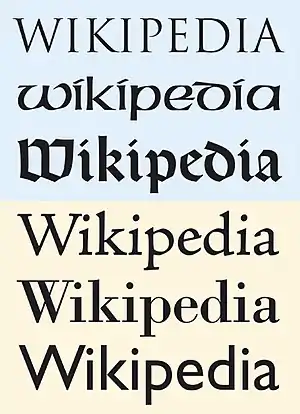
Themen der Typografiegeschichte
- Im Mittelpunkt der Typografiegeschichte steht die historische Herausbildung der unterschiedlichen Druckschriften (Antiqua, Grotesk sowie Displayschriften) bis hin zur heutigen Typografie im Internet. Die Handschriften vor der Erfindung des Buchdrucks hingegen zählt man in der Regel zur Vorgeschichte. Zur historischen Entwicklung der Schrift, siehe auch Geschichte der Schrift und Paläografie.
- Die westliche Typografiegeschichte beschränkt sich naturgemäß auf den Einzugsbereich des lateinischen Alphabets – also West- und Mitteleuropa, Nord- und Südamerika sowie den mittleren und südlichen Bereich des afrikanischen Kontinents. Schwerpunkte sind dabei meist die entwickelten Länder Westeuropas sowie die USA. Zur Entwicklung der unterschiedlichen Alphabete weltweit siehe Schriften der Welt, Alphabet sowie Alphabetschrift.
Ein mit der Geschichte der Typografie eng verwandtes Thema ist die Geschichte des Grafikdesigns sowie die Geschichte der grafischen Stile. Anders als beim Grafikdesign, das allgemeine Gestaltungsgrundsätze thematisiert, steht bei der Typografie mehr der Umgang mit Schriften sowie die typografischen Konventionen im Mittelpunkt. Die Geschichte der Typografie behandelt vor allem
- die historische Entwicklung der Druckschriften,
- technische Innovationen, soweit sie für den Einsatz von Schriften relevant sind (Buchdruck, Blei-, Maschinen- und Fotosatz, Desktop-Publishing; OpenType),
- die historische Herausbildung typografischer Konventionen und Maßsysteme.
Handschriftliche Vorgeschichte der Lateinischen Druckschriften
(siehe ausführlich Paläografie – Geschichte der Lateinischen Schrift)
Vom Aufkommen der Schrift als solcher im Altertum bis zum Beginn des Buchdrucks am Ende des Mittelalters war das Erstellen von Dokumenten und Büchern eine handschriftliche Angelegenheit. Die Gestalt der lateinischen Schrift erfuhr während dieses Zeitraums mehrmalige Veränderungen. Die wichtigsten uns heute bekannten Vorformen der Druckschriften sind: römische Capitalis, frühmittelalterliche Unzialschriften, die Karolingische Minuskel sowie die gotisch-gebrochenen Schriften des Hoch- und Spätmittelalters. Typografiegeschichtlich relevant sind diese Vorformen aus drei Gründen:
- der im Verlauf eines Jahrtausends vollzogenen Zusammenfügung von Groß- und Kleinbuchstaben-Alphabet,
- der formalen Entwicklung hin zu den aktuellen Buchstabenformen und schließlich
- als historisierende Referenzmöglichkeit: Anders als heute noch verwendete Druckschrift-Prototypen wie etwa die Garamond aus dem 16. Jahrhundert dienen digitale Capitalis-, Unzial- oder Textura-Schriften vor allem dazu, historische Epochen typografisch in Szene zu setzen.
Römische Capitalis
Über Etrusker und Griechen gelangten die Vorformen des heutigen lateinischen Alphabets im Verlauf des ersten Jahrtausends v. Chr. zu den Römern. Das römische Alphabet entsprach bereits weitgehend dem heute verwendeten. Allerdings war es ein reines Großbuchstaben-Alphabet. Als Hochschrift des Römischen Reiches gilt heute die Capitalis monumentalis. Bekanntestes historisches Dokument dieser Monumentalschrift sind die Inschriften der 113 n. Chr. errichteten Trajanssäule. Neben den vor allem in Stein gehauenen Monumentalschriften gab es auch informellere Schriftvarianten wie etwa die Capitalis quadrata, die Capitalis rustica sowie die ältere römische Kursive und die jüngere römische Kursive. Neben der Verwendung als Buchschrift dienten sie vor allem dazu, den informellen, alltäglichen Schriftverkehr zu bewältigen.
Unzialschriften
Auch im Römischen Reich unterlagen die Schriften einem langsamen Veränderungsprozess. Die Schriftkultur der Spätantike und des Frühmittelalters war von der Unzialschrift und der Halbunzialen geprägt. Deren Herkunft leitete sich von den informelleren Schreibvarianten der römischen Schrift ab (ältere römische Kursive, jüngere römische Kursive). Im angelsächsischen Bereich wurden für einzelne Laute auch Zeichen aus Runenschriften ergänzt (thorn für th). Die Unzialschrift hat ein Großbuchstaben-Alphabet; die seit dem 3. Jahrhundert verwendete Halbunziale benutzt auch Ober- und Unterlängen, um Buchstaben zu unterscheiden, und besitzt deshalb ein Kleinbuchstaben-Alphabet.
Neben der Unziale und der Halbunziale entwickelten sich aus den römischen Kursiven eine Reihe regionaler Schriftformen. Da sie vor allen lokale Bedeutung genossen, werden sie auch unter dem Oberbegriff Nationalschriften zusammengefasst, wobei ihr Gebrauch nicht ethnisch oder politisch bestimmt ist, sondern vorrangig geografischen Bezug hat. Entwicklungshistorisch sind die Schriften des Frühmittelalters die unmittelbaren Vorläufer der Karolingischen Minuskel.
Die Unziale findet bis heute gern in christlichen Kontexten Verwendung, etwa für Inschriften in Kirchen oder auf Grabsteinen. Moderne Nachinterpretationen der Unzialschrift wie zum Beispiel die American Uncial finden sich im Fantasy-Bereich oder auch in der Esoterik-Szene. Ein bekanntes Einsatzbeispiel ist etwa in der Verfilmung des Tolkien-Bestsellers Der Herr der Ringe zu sehen.
Karolingische Minuskel
Mit Unterstützung der Karolinger, die seit Ende des 8. Jahrhunderts weite Teile Mitteleuropas beherrschten, verbreitete sich die Karolingische Minuskel über ganz Europa. Auslöser für ihre flächendeckende Etablierung waren insbesondere die Bildungsreformen Karls des Großen (die so genannte Karolingische Reform). Am spätesten drang die Schrift in Spanien (Westgotische Minuskel), Großbritannien (Insulare Schriften) und Süditalien (Beneventana, Curialisca) ein.
Die Karolingische Minuskel ist das Vorbild für das Kleinbuchstaben-Alphabet in seiner heute noch gebräuchlichen Form. Die Abschriften antiker Autoren (beispielsweise Horaz, Vergil, Homer) in klösterlichen Scriptorien führte bei den Gelehrten der Renaissance zu der Annahme, es handle sich bei der Karolingischen Minuskel um die originale Schrift der Antike. Ab dem 14. Jahrhundert entstand so auf Basis der Karolingischen Schriften in Italien die Humanistische Minuskel, die zur Vorlage der ersten Renaissance-Druckschriften (Venezianische Renaissance-Antiqua, ab etwa 1470) wurde. In Abgrenzung zu den zeitgenössischen hochmittelalterlichen Schriften (der Textura und der Rotunda) wurde diese Schriftneuschöpfung als „antik“ (lateinisch antiquus) bezeichnet, um sie so gegenüber den später entstandenen Schriften abzugrenzen. Hiervon leitet sich der Begriff „Antiqua“ ab.
Gotische Schriften
Aus der spätkarolingischen Minuskel entwickelten sich im Hochmittelalter die Buchschriften der Gotik. Ihre zahlreichen Varianten zeichneten sich alle durch ein regelmäßiges, strenges, eng geschriebenes Schriftbild aus. Die Rundungen der Buchstaben wurden gebrochen, weshalb diese Schriften auch – insbesondere auch zwecks Unterscheidung zu den später entstandenen Antiqua-Schriften – als gebrochene Schriften bezeichnet werden. Das Hauptmerkmal der gotischen oder gebrochenen Schriften war ein enges, dunkles Schriftbild, das in seiner strukturartigen Form stark an gewebte Stoffe erinnert; daher leitet sich auch der Name Textura für die bekannteste Schrift dieser Epoche ab.
Parallel entwickelte sich in Italien, Spanien und in geringerem Maße in Deutschland eine alternative Form der gotischen Schrift: die Rotunda oder Rundgotische. Bei der rundgotischen Schrift sind die Formen weiter und die Buchstaben besitzen statt der harten Winkel Rundungen. Dies machte die Schrift lesbarer. Beide Schriftarten wurden von den frühen Druckern der sogenannten Inkunabelzeit übernommen. Bis Mitte des 16. Jahrhunderts wurden sie allerdings weitestgehend von anderen Schriften verdrängt.
Eine weitere Entwicklung der hochmittelalterlichen Gotik waren Vorformen der heutigen Kursivschriften. Schräg geschriebene (also: kursive) Schriften wurden dem Gebrauch in Büchern angepasst und so zu den sogenannten Bastarda-Schriften weiterentwickelt. In Mitteleuropa bildete sich als Weiterführung der Textura zum Ende des Mittelalters die Fraktur heraus. Die zu Beginn des 16. Jahrhunderts entstehenden Frakturschriften waren erfolgreich und lieferten auch die Vorbilder für die Schriftentwürfe von Albrecht Dürer und Johann Schönsperger. Eine derbe, volkstümliche Fortentwicklung der Textura ist die Schwabacher, die ebenfalls zu Beginn des 16. Jahrhunderts entstand. Zusammen mit der Fraktur bestimmte sie das Druckbild in Deutschland bis hinein ins 20. Jahrhundert. In den Ländern um das Mittelmeer, dem Hauptverbreitungsgebiet der Rotunda, setzen sich hingegen die Antiqua-Schriften durch.
Geschichte der Druckschriften bis zum 20. Jahrhundert
Anders als die bislang beschriebenen historischen Schrifttypen sind die ab der frühen Neuzeit entwickelten Schriften keine geschriebenen Schriften, sondern Druckschriften. Das Hauptmodell, die ab circa 1450 aufkommende Antiqua, bildet bis auf den heutigen Tag die Grundlage aktuell verwendeter Schriften. Die Feinausgestaltung der Antiquaschriften hingegen durchlief seit der Renaissance-Ära mehrere Entwicklungsstadien. Die Schriftklassifikation unterteilt diese in die Hauptgruppen Renaissance-Antiqua, Barock- oder Übergangsantiqua sowie klassizistische Antiqua. Ab dem 19. Jahrhundert kamen als weitere Schrifttypen serifenbetonte linear Antiqua sowie serifenlose Groteskschriften hinzu.
Entstehung der Antiqua
Im Zuge der Frührenaissance erwachte auch das Interesse an den Schriftformen der Antike neu. Mittelpunkt der Entwicklung war Italien. Anders als im Norden hatte sich hier früh das gemäßigt gotische Modell der Rotunda etabliert. Gutenbergs 42-zeilige Bibel von 1455 hatte noch die besten gotischen Handschriften zum Vorbild. Bereits zehn Jahre später erkannten deutsche Druckmeister in Subiaco (Italien) sowie venezianische Nachfolger wie Nicolas Jenson und Aldus Manutius, dass die neue Technik auch eine andere Formgestaltung ermöglichte. Nach dem Vorbild italienischer Humanistenhandschriften vereinigten sie die „überarbeiteten“ Kleinbuchstaben der karolingischen Minuskel mit den Großbuchstaben der römischen Capitalis. Dadurch entstand eine Zweialphabetschrift, die sich von den gebrochenen Schriften des Hochmittelalters klar abhob – die sogenannte „Antiqua“.
Das Bild der ersten Antiquaschriften war noch stark von mittelalterlichen, gotischen Elementen geprägt. Auch die Entwicklung hin zur heute gebräuchlichen Groß- und Kleinschreibung vollzog sich erst langsam im Lauf der folgenden Jahrhunderte und von Land zu Land verschieden. Zusätzlich integrierten die Schriftentwerfer und Stempelschneider der Renaissance zwei weitere Zeichen-Komponenten in ihre zeitgenössischen Schriften: zum einen das arabische, ursprünglich aus dem indischen Raum stammende Ziffernsystem, zum zweiten Kursivschriften. Bei Letzteren handelte es sich um Bastarda-Varianten, welche einige Schreibmeister des ausgehenden 15. Jahrhunderts an das Erscheinungsbild der Antiqua anglichen. Die auch als „Italics“ bezeichneten Antiqua-Kursiven entwickelten sich erst im Verlauf der folgenden Jahrhunderte zu integrierten Schriftschnitten kompletter Schriftfamilien.
Renaissance (1400 bis 1600)
Die Renaissance-Antiqua (andere Bezeichnungen: Old Style-Antiqua oder auch ältere Antiqua) lässt sich in zwei stilistisch klar voneinander abgrenzbare Gruppen aufgliedern: die Venezianische Renaissance-Antiqua und die Französische Renaissance-Antiqua.
Bei der venezianischen Renaissance-Antiqua, deren Stilmerkmale sich ungefähr zwischen 1455 und 1485 entwickelten, ist die Ableitung von spätmittelalterlichen Rotunda- und Bastarda-Schriften noch mehr oder weniger stark zu erkennen. Bekanntestes Exponat dieser Gruppe ist die von Nicolas Jenson um 1470 geschaffene Jenson Antiqua; eine zeitgemäße Interpretation ist die 1996 entstandene Adobe Jenson von Robert Slimbach. Die Strichstärken dieses Typs sind relativ einheitlich. Die kalligrafische Zeichnungsweise tritt klar hervor. Anders als spätere Antiquaschriften erwecken Frühantiquas dieses Typs einen mehr oder weniger stark ausgeprägten historisierenden, spätmittelalterlichen Eindruck und kommen daher im heutigen Satz eher seltener zum Einsatz.
Ihre heute noch gültige, klassische Form erreichte die Antiqua mit dem venezianischen Verleger Aldus Manutius und seinem Stempelschneider Francesco Griffo. Die nach einem zeitgenössischen Kardinal benannte und um das Jahr 1495 entstandene Bembo gilt als der Prototyp dieser Phase. Vor allem im Buchsatz kommt sie bis heute regelmäßig zur Anwendung. Eine weitere Innovation von Griffo war die Entwicklung der Kursivschrift. Insgesamt werden die zwischen Ende des 15. und Anfang des 16. Jahrhunderts geschaffenen Schriften, obwohl großteils in Italien entstanden, bereits dem Modell der Französischen Renaissanceantiqua zugerechnet. Einige Schrifthistoriker bezeichnen die italienischen Schriften der Frühneuzeit auch als „Aldinen“ – als Abgrenzungsbegriff zu den im 16. Jahrhundert entstandenen Typ der Garalden, welcher die Schriften aus der Ära Claude Garamonds charakterisiert.
Der Pariser Stempelschneider Claude Garamond (1499 bis 1561) gilt heute als bekanntester Vertreter der französischen Renaissance-Antiqua. Bis zum Jahr 1600 war die von ihm entworfene Schrift zur vorherrschenden Buchschrift in Europa geworden. Sie zeichnet sich durch ein ruhiges, harmonisches und helles Schriftbild aus und hat ausgeprägte Ober- und Unterlängen. Wegen ihrer formalen Qualitäten und guten Lesbarkeit wird sie auch heute noch oft verwendet und in unterschiedlichen Nachschnitten von zahlreichen Schriftherstellern angeboten. Ein Zeitgenosse Garamonds war der in Lyon ansässige Stempelschneider Robert Granjon (1513 bis 1589). In Anlehnung an historische Schreibschriften versuchte Granjon unter anderem das ambitionierte Schriftprojekt Lettre de Civilité. Die als neue französische Allgemeinschrift geplante Civilité scheiterte allerdings aufgrund mangelnder Akzeptanz.
Barock (1600 bis 1760)
Zu Beginn des 17. Jahrhunderts verlagerte sich das Zentrum der Schriftentwicklung zunehmend in die Niederlande. Maßgebliche Initiatoren waren die beiden Kaufleute und Verleger Christoffel Plantijn (1520 bis 1589) sowie der 1540 geborene Louis Elzevir. Der in Antwerpen ansässige Plantijn besorgte sich zahlreiche Matrizen und Vorlagen aus der Hinterlassenschaft Garamonds; angestellt war bei ihm unter anderem der französische Stempelschneider Jakob Sabon (oder Jacques Sabon; * 1535, † zwischen 1580 und 1590). Für das von Elzevir gegründete Unternehmen in Leiden (später: Den Haag) arbeitete unter anderem Christoffel van Dijck (1601 bis 1699), einer der bedeutendsten Stempelschneider seiner Epoche. Weitere maßgebliche Schriftentwerfer des 17. Jahrhunderts sind der Deutsche Anton Janson sowie der Ungar Mikolós Tótfalusi Kis (auch Miklós Tótfalusi Kis oder Nicholas Kisz; 1650–1702). Für das 18. Jahrhundert ist schließlich der Nürnberger Johann Michael Fleischmann (1701–1768) aufzuführen, der zeitweilig ebenfalls in den Niederlanden tätig war.
Allgemein vollzog sich der Übergang zwischen den Schriften Garamonds und den holländischen Antiquaschriften langsam und kontinuierlich – weswegen die Schriften dieser Epoche auch als Übergangsantiqua bezeichnet werden. Die niederländischen Schriften wirkten einfach, oft derb-robust und erwiesen sich vor allem als gebrauchstüchtig. Digitale Nachschnitte der Schriften von Janson, Van Dijck, Kisz und Fleischmann kommen im Buchsatz ebenfalls nach wie vor regelmäßig zur Anwendung. Die Plantin, eine Reminiszenz an die niederländischen Barockschriften von dem US-amerikanischen Schriftentwerfer Frank Hinman Pierpont (1860–1937) aus dem Jahr 1913, diente schließlich als Vorlage beim Entwurf der wohl bekanntesten Barockantiqua überhaupt – der 1931 bis 1935 entstandenen Times.
Im Vergleich zu den älteren Renaissance-Antiquaschriften wirken die niederländischen und britischen Übergangsantiqua des 17. und 18. Jahrhunderts zum einen nüchterner. Zum anderen treten die Kontraste zwischen Grund- und Haarstrichen allmählich mehr und mehr in den Vordergrund; die Schriften wirken insgesamt kontrastreicher. Ein wesentlicher Grund für diese Entwicklung: Anders als bei den mit der Breitfeder gezeichneten Schriftentwürfen des 16. Jahrhunderts ließen sich die Schriftgestalter des 17. und 18. Jahrhunderts immer stärker von den präzisen Formen zeitgenössischer Kupferstiche inspirieren.
Formal zum Abschluss gebracht wird die Barock- oder Übergangsphase der Antiqua durch die britischen Schriften des 18. Jahrhunderts. Anfangs orientierten sich deren Gestalter stark an holländischen Vorbildern. Bekanntester Schriftentwerfer dieser Epoche war William Caslon. Stilistisch gesehen brachten Caslons Schriften wenig Innovationen. Dafür waren sie beliebt und schließlich so verbreitet, dass sie sowohl beim britischen Königshaus Anwendung fanden als auch bei der Abfassung und Verbreitung der US-amerikanischen Unabhängigkeitserklärung. Caslons Epigone war der britische Drucker und Stempelschneider John Baskerville. Im Unterschied zu Caslon galt Baskerville als Perfektionist; seine kontraststarken, stark vom Kupferstich geprägten Schriften wie die Baskerville beeinflussten schließlich auch die klassizistischen Schriftentwerfer stark.
Klassizismus (1760 bis 1830)
Im Klassizismus erreichte die Entwicklung der Antiqua ihren vorläufigen Endpunkt. Die Buchstaben wurden aufgrund der technischen Weiterentwicklung immer kontrastreicher, die Serifen immer zarter. Schriften wurden mit Lineal und Zirkel konstruiert, um dem Ideal von Klarheit und Norm zu genügen. Aufgrund dessen sind sie aber auch wesentlich schwerer zu lesen als ihre Vorgänger aus der Renaissance und dem Barock. Blocksatz und Mittelachse blieben als Formen der Typografie weiterhin erhalten. Aufgabe der Typografen war die Wahl einer passenden Schrift und die Strukturierung des Textes. Buchschmuck wurde sparsam eingesetzt. Üppig illustrierte Initialen wichen Initialen in der Grundschrift. Am Ende des Klassizismus tauchten die ersten Grotesk- und Egyptienne-Schriften auf. Eine weitere Innovation dieser Ära war schließlich die Etablierung des typografischen Punktsystems.
Die bedeutendsten Schriftentwerfer der Epoche waren der Italiener Giambattista Bodoni, die französische Stempelschneiderfamilie Didot sowie der Deutsche Justus Erich Walbaum. Insbesondere Bodonis Schriften, dokumentiert in dem nach seinem Tod herausgegebenen Manuale Tipografico, gelten aufgrund ihrer Präzision und ihrer Eleganz als herausragend. Firmin Didots gleichnamige Didot hingegen wird wegen ihrer abgespeckt-kühlen, oft auch als kalt charakterisierten Präzision als die Schrift der französischen Aufklärung bezeichnet. Darüber hinaus dominierte das Familienunternehmen Didot mit seinen Schriften und Gestaltungen die französische Typografie bis weit ins 19. Jahrhundert. Die Walbaum, der dritte Prototyp der klassizistischen Ära, wird hingegen oft als gemütlich, negativ auch als biedermeierlich beschrieben. In Deutschland avancierte sie indes zur maßgeblichen Schrift der klassizistischen und romantischen Epoche.
Die Gestaltungsmerkmale klassizistischer Antiquaschriften wurden zu Anfang des 19. Jahrhunderts auch auf das Erscheinungsbild der Fraktur übertragen, die das typografische Erscheinungsbild in Deutschland weiterhin maßgeblich prägte. Neben Walbaum war an dieser stilistischen Erneuerung auch der Drucker Johann Friedrich Unger beteiligt. Walbaum Fraktur und Unger Fraktur entwickelten sich schließlich zu Vorbildern für weitere Frakturentwürfe der Wilhelminischen Ära, wie zum Beispiel die Fette Fraktur oder die 1911 entstandene Wilhelm Klingspor Gotisch. Auch bei anderen Schrifttypen wie zum Beispiel den aus den Kanzleischriften hervorgegangenen Schreibschriften wurden die klassizistischen Einflüsse immer unübersehbarer. In der ersten Hälfte des 19. Jahrhunderts tendierte die klassizistische Typografie immer stärker zu rein formalen und immer ausgeschmückteren Lösungen. Stilgeschichtlich mündete die klassizistische Phase der Typografie schließlich in den stark mit Pomp und Pathos aufgeladenen Historizismus der Viktorianischen Epoche.
Die Ära der Industrialisierung (1830 bis 1890)
Das 19. Jahrhundert brachte stilistisch wenig grundlegende Innovationen. Die wesentliche Neuerung war das Aufkommen serifenverstärkter Schriften. Vorläufer waren sogenannte Egyptienne-Schriften, die bereits zu Anfang des 19. Jahrhunderts verstärkt zum Einsatz kamen. Ihr Name leitet sich vermutlich aus der Orientbegeisterung der napoleonischen Ära ab, die wiederum durch den Ägyptenfeldzug Napoleons ausgelöst worden war. Serifenverstärkte Schriften wie zum Beispiel die Clarendon aus dem Jahr 1845 hingegen waren in der Regel Zeitungsschriften, deren Serifen verstärkt wurden, damit sie im Druck nicht ausbrachen. Stilistisch wirkten die Serifenverstärkten der Jahrhundertmitte sehr robust und wiesen ansonsten meist mehr oder weniger starke klassizistische Gestaltungsmerkmale auf. In der Folgezeit änderte sich dies: Durch das Übertragen der Gestaltungsmittel Serifenverstärkung und Serifenanhängung auf immer mehr Schrifttypen bildete sich im Verlauf des 20. Jahrhunderts nach und nach eine eigenständige Zwischengruppe in sich recht heterogener Schriften heraus. Mittlerweile werden Slab Serifs oder Serifenverstärkte in den meisten aktuellen Schriftklassifizierungssystemen als eigenständige Gruppe geführt – neben den beiden anderen Hauptgruppen Serif (traditionelle Antiqua-Schriften) und Sans Serif (serifenlose Groteskschriften wie zum Beispiel die Helvetica).
Innovativ war das 19. Jahrhundert vor allem in technischer Hinsicht. Maschinelle Fertigungsprozesse veränderten sowohl den Druck als auch die Illustrationsgrafiken. Das Bebildern von Drucksachen ließ sich erheblich standardisieren durch die von Alois Senefelder erfundene Technik der Lithografie. Eine weitere Erfindung war schließlich die Fotografie, deren Etablierung Ende des Jahrhunderts zu den ersten einfachen Rasterungs- und Reproduktionsverfahren führte. Für eine wachsende Nachfrage nach Druckprodukten sorgte die allmähliche Herausbildung einer modernen Massengesellschaft. Dies führte in der Buchgestaltung oftmals dazu, dass sich das Buch als Massenprodukt in seiner Typografie an den Handwerksstücken des Barock orientierte. Eine überreiche Ausstattung mit Zierelementen zeugt davon. Neben dem traditionellen Buchdruck entwickelten sich Ansätze einer Zeitungslandschaft sowie ein breiter Markt für Publikationen, Werbedrucke und Plakate jeglicher Couleur. Die Herausforderungen hatten sich gewandelt: Waren Druck und Typografie jahrhundertelang ein überschaubares Handwerk geblieben, hatten sie sich nunmehr den Herausforderungen einer industriell bestimmten Massengesellschaft zu stellen.
Blei- und Fotosatz im 20. Jahrhundert
Die rund 90 Jahre zwischen 1890 und 1980 prägen das Bild der Typografie bis in die Gegenwart hinein. Das Druckhandwerk wurde zur Industrie, und auch die Typografie wurde zu einem Teil davon. Sowohl stilistisch als auch technologisch verlief diese Epoche teilweise recht turbulent. Maßgeblich waren dabei folgende neuen Entwicklungen:
- Herstellung und Anwendung von Schriften wurden immer stärker von industriellen Fertigungsmethoden bestimmt. Wesentliche Stationen dieses Prozesses waren die Erfindung der Bleisatzmaschine durch Ottmar Mergenthaler (Linotype-Modell, 1886) und Tolbert Lanston (Monotype-Modell, 1887), einige Jahrzehnte später das Aufkommen des Fotosatzes. Folge: Erfassung und typografische Gestaltung des Textes ließ sich in immer stärkerem Maß über tastaturgesteuerte Mechanismen vornehmen anstatt von Hand.
- Ein Folgeaspekt des Industrialisierungsprozesses war die bis dahin ungekannte Anzahl und Verbreitung neuer Schriften. Ob digitale Varianten von Garamond und Bodoni oder neue, zeitgemäße Schriftentwürfe wie Futura, Times und Helvetica: Fast alle aktuell verwendeten Schriften stammen entweder aus der anschließenden und bis heute andauernden Computersatz-Ära oder basieren auf Entwürfen dieser Epoche. Grundlage war die Herausbildung großer Schriftgießereien und Schrifthersteller. Folge: Erfolgreiche Schriften konnten so rasch den Status einer Markenware erlangen – und waren damit wiederum in der Lage, ihrerseits Produkten oder Publikationen ein unverwechselbares „Branding“ zu verleihen.
- Neben der traditionellen Buchtypografie entwickelte sich das Grafikdesign als mehr oder weniger eigenständige Sparte. Das nicht spannungsfreie Wechselverhältnis dieser beiden Sparten bestimmte auch die stilistische Entwicklung der Typografie des 20. Jahrhunderts nicht unmaßgeblich mit.
Jugendstil und Neue Buchkunst
Die modernen Kunststile seit dem Impressionismus fanden auch in der Grafik und der Typografie ihren Widerhall. Populär wurde ab 1890 der Jugendstil. Seine floralen Zierelemente, die geschwungenen Formen sowie die grafikbetonte Ausführung inspirierten auch die Schriftentwerfer der Jahrhundertwende. Eine bekannte Jugendstil-Schrift war die Eckmann, entworfen vom Grafiker Otto Eckmann; darüber hinaus äußerte sich der Jugendstil-Einfluss auch in zahlreichen Buchillustrationen und Exlibris-Gestaltungen.
Insgesamt machte sich um die Jahrhundertwende eine Rückbesinnung zu den Wurzeln der Buchkunst immer stärker bemerkbar. Angestoßen wurde diese von dem britischen Typografen, Sozialisten und Kleinpressen-Verleger William Morris sowie von dem sich auf ihn berufenden Arts and Crafts Movement. Im Wesentlichen initiierte diese Bewegung drei Dinge: eine Rückbesinnung auf die Antiqua-Modelle der Renaissance, Klarheit und Einfachheit in der Buchillustration sowie überschaubare handwerkliche Prozesse bei der Erstellung von Drucksachen. Eine unmittelbare Folge des Arts and Crafts-Bewegung war die Entstehung einer Kleinpressenbewegung, die mehr oder weniger den Morris’schen Idealen verpflichtet war und deren Überbleibsel teilweise bis in die Gegenwart herüberragen. Ein etablierter Treffpunkt dieser Szene in Deutschland ist etwa die Mainzer Minipressen-Messe, die aktuell im zweijährlichen Turnus stattfindet.
Stark vom Arts and Crafts-Movement beeinflusst war insbesondere die Strömung der Neuen Buchkunst, die sich im Jahrzehnt vor dem Ersten Weltkrieg herauszubilden begann. Die jungen Schriftentwerfer der Vorkriegszeit, darunter Fritz Helmuth Ehmcke und Friedrich Wilhelm Kleukens, verwarfen sowohl den typografischen Spätklassizismus als auch den Zierrat des populären Jugendstils. Neues Ideal wurde eine aufgeräumte, schnörkellose und stark den Ideen der Renaissance verpflichtete Buchtypografie. Walter Tiemann in Leipzig, F. H. Ernst Schneidler in Stuttgart und Rudolf Koch in Offenbach waren als Ausbilder die maßgeblichen Mentoren dieser Form der Typografie. Im Buchsatz blieb sie bis weit nach dem Zweiten Weltkrieg bestimmend.
Siehe auch: Buchkunstbewegung
Etablierung der Groteskschriften
Der Beginn des 20. Jahrhunderts war auch die Geburtsstunde des bis heute letzten wichtigen Schrifttyps: der serifenlosen Grotesk. Ihr Ursprung lässt sich zwar bis zum Ende des 18. Jahrhunderts zurückverfolgen, flächendeckend eingesetzt wurden Groteskschriften jedoch erst seit dem Aufkommen der Werbung. Dass der neue Schrifttyp auf viele Zeitgenossen polarisierend wirkte, stellt insbesondere die noch aus dem frühen 19. Jahrhundert stammende Bezeichnung „Grotesk“ unter Beweis. Zwei frühe Grotesk-Modelle waren die von der Berliner Schriftgießerei Berthold in Serie gegebene Akzidenz Grotesk von 1904 sowie die US-amerikanische Franklin Gothic von Morris Fuller Benton. Ähnlich wie bei den Antiqua-Schriften entwickelten sich auch bei der Grotesk mit der Zeit unterschiedliche Design-Richtungen:
- eine stark an der klassizistischen Formenlehre orientierten Schule. Zu ihr zählen neben den beiden erwähnten Schriften vor allem die Helvetica, die Arial und die Univers. In seiner reinsten Form ist dieser Gestaltungsstil bei den drei letzten Schriften zu beobachten; zeitlich gesehen überschneidet er sich stark mit der zeitweiligen Dominanz helvetischer Gestaltungskonzepte in den 1950er und 1960er Jahren. Als gemäßigte Form dieser Richtung gilt die Amerikanische Grotesk wie zum Beispiel die Franklin Gothic.
- eine von der Renaissance-Antiqua abgeleitete Schule. Hauptmerkmal dieser Gestaltungsschule sind kalligrafische, meist freiere Gestaltungsmethoden sowie leicht variierende Strichstärken. Populär wurde dieser Typ der Grotesk vor allem durch Edward Johnston (Johnston Sans), den Gestalter der Londoner U-Bahn-Beschilderung sowie die Gill Sans von Eric Gill, die Ende der 1920er Jahre erschien. Auf lange Sicht entwickelte sich dieser auch als „humanistisch“ bezeichnete Typ zum erfolgreichsten und am häufigsten angewandten Modell.
- eine geometrisch-konstruktivistische Schule. Sie hatte ihre Höhepunkte vor allem im Umfeld der Elementaren Typografie in den 1920er Jahren. Bekannteste Vertreterin dieser Richtung ist die Futura von Paul Renner sowie die auch als Bauhaus bekannte Universalschrift des Bauhaus-Typografen Herbert Bayer. Spätere Reminiszenzen wie etwa die Avant Garde aus dem Jahr 1970 spielten vor allem in der Zeitgeist- und Modetypografie eine Rolle. Als Stilzitat gern verwendet werden geometrische Konstruktionselemente darüber hinaus auch in postmodernen Schriften.
Vor allem in der Werbung wurde der neue Schrifttyp rasch populär. Im weiteren Verlauf des 20. Jahrhunderts setzten sich Groteskschriften (Sans Serifs) immer stärker durch und gelten heute – neben Antiquas (Serif-Schriften) und Serifenverstärkten (Slab Serifs) – als dritter Grundtyp im Bereich der Textschriften.
Avantgarde und Elementare Typografie
Stark verwendet wurden die neuen Groteskschriften vor allem im Rahmen der Elementaren Typografie ab Mitte der 1920er Jahre. Die Elementare oder auch Neue Typografie war den Konzepten des Bauhauses stark verbunden. Ihre Ursprünge lassen sich vor allem auf Strömungen der zeitgenössischen Avantgarde zurückführen. Die zeitgenössischen Kunstrichtungen Expressionismus, Dadaismus sowie der russische Konstruktivismus beeinflussten auch die Typografie nach dem Ersten Weltkrieg recht stark. Der Einfluss des Expressionismus machte sich vor allem in der Buchgestaltung bemerkbar. Er inspirierte teilweise auch das Schaffen traditionsverbundener Schriftgestalter wie zum Beispiel die Offenbacher Schule um Rudolf Koch. Dadaismus und Konstruktivismus hingegen hinterließen ihre Spuren vor allem in der Grafik-Kunst, in Gebrauchsdrucksachen, politischen Aufrufen und schließlich der Plakatgestaltung. Zu erwähnen sind hier die beiden Grafikkünstler Kurt Schwitters und John Heartfield.
Vom Konstruktivismus beeinflusst war darüber hinaus die niederländische Grafikgruppe De Stijl (Theo van Doesburg) sowie das 1919 von dem Architekten Walter Gropius gegründete Bauhaus. Das Bauhaus vereinte unterschiedliche Ansätze aus Architektur, Industriedesign, Kunst, Grafikdesign und Typografie zu einem betont modernistischen Ansatz. Seit ihrer Gründung war die Institution umstritten. Fortwährende Angriffe der politischen Rechten führten 1925 zum Umzug von Weimar nach Dessau, 1932 schließlich zur erneuten Umsiedlung nach Berlin. Wesentlich geprägt wurde das grafische Konzept des Bauhauses von dem gebürtigen Ungarn Lázló Moholy-Nagy sowie den Grafikern Joost Schmidt, Josef Albers und Herbert Bayer. Bayer entwarf Mitte der Zwanziger die später als Bauhaus bekannte Universalschrift.
Die Neue Typografie entwickelte sich während der 1920er und frühen 1930er Jahre zu einer ebenso einflussreichen wie polarisierenden Strömung. Wesentliche Gestaltungselemente waren Groteskschriften, geometrische Formen, der kollagehafte Einsatz von Fotoelementen, Layoutraster sowie die Propagierung der radikalen kleinschrift, die 1925 auch in den Bauhaus-Publikationen eingeführt worden war. Zum Wortführer und Theoretiker der Elementaren Typografie avancierte Jan Tschichold; stark von ihren Gestaltungskonzepten beeinflusst ist auch die 1928 entstandene Futura von Paul Renner, die sich aus dem Umfeld des Neuen Frankfurt zu einer der meistverkauften Schriften aller Zeiten entwickelte. Zwangsweise beendet wurde das Intermezzo der typografischen Moderne durch die Machtergreifung der Nationalsozialisten 1933. Eine Reihe Grafikkünstler und Schriftentwerfer, darunter auch Jan Tschichold und Herbert Bayer, gingen aus politischen und existenziellen Gründen ins Exil. Andere waren aufgrund der zunehmenden rassistischen Repressalien zur Flucht genötigt; wieder andere, wie etwa Paul Renner, mussten erhebliche berufliche Einschränkungen hinnehmen oder wählten von sich aus den Weg der Anpassung. In der Epoche der Weimarer Republik war die Erklärung, sich einer bestimmten typografischen Schule zugehörig zu fühlen, oft verbunden mit dem Ansatz, den Menschen mit den Mitteln der eigenen Typografie zu beeinflussen. Der Fraktur-Antiquastreit erlebte in den 1920er Jahren einen ersten Höhepunkt.
Die konservative Ära der Dreißiger
International war die Dekade der Dreißiger vorwiegend von konservativen sowie gemäßigt modernen Ansätzen geprägt. In der Buchgestaltung hatte sich die Neue Buchkunst zum internationalen Standard entwickelt. In der Werbung sowie in der Plakatkunst hingegen machte sich der Einfluss des Art Déco immer stärker bemerkbar. Der Art déco griff das Dekorative, Ornamentale des Jugendstils auf und schuf auf der Grundlage konstruktivisch-geometrischer Gestaltungselemente einen ebenso gefälligen wie mondänen, modern wirkenden Gestaltungstil. Auch im Bereich der Werbeschriften war sein Einfluss unübersehbar. Einige noch heute verwendete Schriften dieser Epoche sind etwa die Broadway, die Binner sowie die Peignot.
In den westeuropäischen Ländern führte die Rückbesinnung auf typografische Traditionen vor allem zur Entwicklung neuer Textschriften. Die wohl bekannteste ist die Times. Sie entstand Anfang der 1930er Jahre anlässlich eines Relaunches der gleichnamigen britischen Zeitung. Eine weitere bekannte Schrift dieser Epoche ist die Rockwell. In den USA führte die Ankunft zahlreicher europäischer Exilanten zu einer spürbaren Modernisierung des Grafikdesigns. Lázló Moholy-Nagy gründete 1937 in Chicago das New Bauhaus; nach dem Zweiten Weltkrieg beeinflusste die vom Bauhaus inspirierte bildhafte Typografie die Werbegestaltung. Diese wiederum wirkte über die Schweizer Gestaltungschule der Fünfziger und Sechziger stark auf Europa zurück.
.png.webp)
In Deutschland wurde die Situation wesentlich durch die traditionelle Zweischriftigkeit geprägt. Der Streit zwischen Anhängern der Fraktur und Anhängern der Lateinschrift reichte im Prinzip zurück bis in die Ära der Reformation. Initiativen zur Übernahme der als Lateinschrift bezeichneten Antiqua, vorgetragen unter anderem durch Abgeordnete der SPD und der liberalen Fraktionen, scheiterten im Reichstag des Kaiserreiches wiederholt. Die im Verlauf des 19. Jahrhunderts von der politischen Rechten als Deutsche Schrift politisierte Fraktur war bis weit in die 1930er Jahre hinein der dominierende Schrifttyp: Nach 1928 wurde über die Hälfte aller in Deutschland erschienenen Buchtitel in Fraktur gedruckt. Die lateinische Schrift fand vor allem in wissenschaftlichen Publikationen und Gebieten der Kunst und Technik ihre Anwendung. Die Frakturschrift hingegen fand sich in fast allen Schul- und Kinderbüchern, sowie der klassischen und volkstümlichen Literatur wieder, welche oft mit einer sehr hohen Auflagenzahl erschienen. Zusammengenommen betrug die Stückzahl der Bücher in deutscher Druckschrift so schätzungsweise 90 Prozent oder sogar noch mehr.
Von politischen Gegnern auch als „Schaftstiefelgrotesk“ verspottet, etablierten sich in den frühen Dreißigern zudem Gebrochene-Grotesk-Schriften mit teilweise martialischen Namen wie zum Beispiel Tannenberg, National oder Deutschland. Mit dem sogenannten „Normalschrifterlass“ vollzog das nationalsozialistische Regime 1941 eine unerwartete Kehrtwendung. Versuchten in den Jahren zuvor noch zahlreiche Fachleute den Nachweis zu erbringen, dass nur gebrochene Schriften „wahrhaft deutsch“ seien, wurden diese in einem von Martin Bormann unterzeichneten Erlass plötzlich als „Schwabacher Judenlettern“ diffamiert und der Einsatz von Antiqua-Schriften als verbindlich vorgeschrieben. Die beiden Typografieexperten und Zeitzeugen Hans Peter Willberg und Albert Kapr halten als mögliche Gründe für diese unerwartete Umstellung pragmatische Gründe für am wahrscheinlichsten: Die Machthaber des Dritten Reiches benötigten eine Verkehrsschrift, die auch in den von ihnen besetzten Teilen Europas verstanden werden konnte. Für diese Aufgabe erwies sich die Fraktur als ungeeignet. Trotzdem konnte sich die Fraktur aufgrund ihrer Vorgeschichte von ihrem rechten, deutschtümelnden Nimbus bis heute nicht mehr freimachen. Folge: Sowohl in der Bundesrepublik als auch in der DDR wurde nach dem Zweiten Weltkrieg allgemein die Antiqua als Verkehrsschrift übernommen.
Nachkriegstypografie und Schweizer Funktionalismus
Die Nachkriegstypografie in Deutschland war zunächst konservativ und Buchkunst-dominiert. Ein typografischer Neuanfang erfolgte erst allmählich. Durch innovative, nichtsdestoweniger jedoch klassische neue Schriften von sich reden machte vor allem der Darmstädter Hermann Zapf (Palatino, 1948 und Optima, 1964); zu erwähnen sind weiterhin Georg Trump sowie Jan Tschichold. Tschichold lebte mittlerweile in der Schweiz und hatte sich dort zu einem entschiedenen Fürsprecher der traditionellen Buchtypografie gewandelt. Seine zahlreichen Publikationen weisen ihn bis heute als einen der bedeutendsten Typografen des 20. Jahrhunderts aus. Seine 1967 erschienene Garamond-Nachinterpretation Sabon ist im Genre Buchsatz weitverbreitet.
In der Schweiz entwickelte sich in den 1950er Jahren eine neue, stark vom Bauhaus sowie dem zeitgenössischen Industriedesign geprägte Typografieauffassung. Ihre in vielerlei Hinsicht Wissenschaftscharakter beanspruchenden Hauptmerkmale waren typografiedominierte Gestaltungen, großzügige Verwendung von Weißräumen, geometrische Layoutanordnungen, die stringente Anwendung von Gestaltungsrastern sowie der Einsatz neutral wirkender, sachlicher Groteskschriften. Führende Grafiker und Typografen der Schweizer Gestaltungschule waren u. a. Josef Müller-Brockmann, Emil Ruder oder Max Bill. Als funktionalistische Schriften berühmt wurden vor allem die Helvetica der Haas’schen Schriftgiesserei in Basel sowie die Univers von Adrian Frutiger (beide 1957). Die Univers war als Gegenstück zur Helvetica entstanden; Frutiger definierte die Laufweiten und Dickten seiner Schrift anhand eines Zahlensystems. In Deutschland selbst wurden die funktionalistischen Typografiekonzepte maßgeblich von der Hochschule für Gestaltung Ulm (HfG) sowie ihrem Gründer Otl Aicher befördert. Von Aicher, der vor allem durch seine Arbeiten in den Bereichen des Corporate Design und der Entwicklung von Piktogrammen und Leitsystemen bekannt wurde, stammt auch der Ende der 1980er Jahre bei AGFA erschienene Schriftclan Rotis. Vor allem in der Unternehmenskultur fanden die funktionalistischen Typografiekonzepte breiten Widerhall. Die sachlich-schmucklose Gestaltungsweise der Schweizer Schule rief seit den Sechzigern allerdings zahlreiche Gegenbewegungen auf den Plan – insbesondere aus dem Bereich der Jugend- und Popkultur.
Werbeschriften und Fotosatz
Der Einfluss von Fluxus, Pop Art sowie der psychedelische Stil der Hippie-Jugendsubkultur dokumentierte sich insbesondere in den Werbeschriften der 1960er, 1970er und 1980er Jahre. In den 1960ern erlebten manche Schriften des Jugendstils und der Art déco eine Renaissance im Posterdesign. Federführend bei der Entwicklung von Schriften für Headlines, Plakaten und Außenwerbungen wurden die britische Firma Letraset sowie die in New York ansässige International Typeface Corporation (ITC). Mit Herb Lubalin, Tom Carnase sowie dem Grafiker und ehemaligen Jazzmusiker Ed Benguiat versammelte die ITC die besten Displayschriften-Gestalter dieser Dekade. Von Lubalin und Carnase stammte die Mode- und Zeitgeist-Groteske Avant Garde; Benguiat lieferte mit den Entwürfen zu ITC Souvenir (1972) und ITC Tiffany (1974) zwei der beliebtesten Werbeschriften der Siebziger. Auch die Textschriften dieser Ära wiesen oft eine ungewöhnliche gestalterische Note auf: so etwa die Eurostile des Italieners Aldo Novarese (1962) oder die Antique Olive des französischen Grafikers und Schriftentwerfers Roger Excoffon (1969). Weitere bekannte Schriftdesigner der 1970er und 1980er Jahre waren u. a. Milton Glaser mit der Glaser Stencil oder Seymour Chwast.
Eine wesentliche Voraussetzung für die Verbreitung explizit fürs Grafikdesign vorgesehener neuer Schriften war der Fotosatz, der ab Anfang der 1970er Jahre den althergebrachten Bleisatz mehr und mehr ersetzte. Die wesentliche Neuerung bestand darin, dass die Textbestandteile einer Drucksache nicht mehr aus Bleilettern oder -zeilen zusammengesetzt wurden, sondern über reprografische Belichtungstechniken gewonnen wurden – ähnlich wie in der Fotografie. Erfindung und erste Experimente mit der Fotosatztechnik lagen zwar bereits einige Jahrzehnte zurück. Die Fotosatzgeräte der Siebziger und Achtziger wurden jedoch zunehmend mit Bestandteilen aus der Computertechnologie aufgestückt und so auch für den Mengensatz immer produktionstauglicher. Eine weitere Erfindung der Zeit waren Abreibebuchstaben, wie sie besonders durch die britische Firma Letraset vermarktet wurden. Eine fundamentale Veränderung erfuhren die Genres Satz und Typografie ab Mitte der Achtziger schließlich durch das neu aufkommende Desktop-Publishing (DTP). Die sogenannte DTP-Revolution der 1980er und 1990er Jahre krempelte sämtliche Produktionsweisen innerhalb der Medienproduktion um und schuf auch im Bereich Typografie die technischen Grundlagen, welche bis heute Gültigkeit haben.
Siehe auch: Reprotechnik
Die DTP-Ära
Ab Mitte der Achtziger verlagerte sich der Satz von Medienprodukten in immer stärkerem Ausmaß auf so genannte Desktopcomputer. Anfangs noch von zahlreichen technischen Kinderkrankheiten belastet und eingeschränkt durch notorische Knappheit an Arbeitsspeicher (RAM), Speicherplatz sowie relativ langsame Prozessoren, hatten sich die Home-Computer in der Medienproduktion bereits Mitte der 1990er Jahre allgemein etabliert. Sie zeichneten sich durch folgende Innovationen aus:
- visuell orientierte Betriebssysteme (Mac OS von Apple und Windows) und Maus-basierende Arbeitsmethoden nach dem Motto: „What you see is what you get“, im DTP-Fachjargon auch WYSIWYG genannt,
- Zusammenführung von Satz, Grafik und Bildgestaltung, mit der sich das Berufsbild des Schriftsetzers zunehmend zu dem des heutigen Mediengestalters wandelte,
- die „Neuen Medien“ wie zum Beispiel das Internet, mit denen multimediale Anwendungsmöglichkeiten für Schriften und Text einen immer größeren Stellenwert erhalten,
- übergreifende, allgemein einsetzbare Schriftformate wie PostScript und TrueType, die die proprietären Schriftformate im Fotosatz vollständig ersetzten und in der Folge für eine noch nie da gewesene Fülle an Schriften sorgten (eine Weiterentwicklung ist das auf 16 Bit und Unicode basierende Format OpenType).
Erste Computerschriften
Eine wesentliche Voraussetzung für den Siegeszug des Desktop-Publishing war die Etablierung spezieller Schriftformate, die sich auf Desktopcomputern nutzen ließen. Am Anfang wurden Bitmapschriften (auf Rastergrafikbildschirmen) und Vektorschriften (Umriss-Schriften bzw. Outlineschriften auf Vektorgrafikbildschirmen und zur Ausgabe auf Stiftplottern) verwendet. Eine wesentlich bessere Skalierbarkeit als Rasterschriften ermöglichte das vom kalifornischen Hersteller Adobe entwickelte Format PostScript. Vorteile: Die Verwendung der jeweiligen Fontdateien war lediglich noch durch das verwendete Betriebssystem eingeschränkt, angeschlossene Belichtungsgeräte waren für den Satz nicht mehr unbedingt erforderlich. Ein weiteres universell einsetzbares Schriftformat war das von Apple und Microsoft entwickelte TrueType-Format, welches unter Windows und in Home-Office-Umgebungen bis heute vorherrschend ist, weil die Fonts frei skalierbar sind und im Gegensatz zu den PostScript-Fonts nur eine Datei benötigen.
Die Entwicklung neuer bzw. die Portierung eingeführter Blei- und Fotosatzschriften in die neuen Computerfontformate PostScript und TrueType veränderte die Szene der Anbieter ab Mitte der Achtziger entscheidend. Computerfirmen wie Adobe bauten ihre Schriftbibliotheken in rascher Folge aus und bedeuteten die Götterdämmerung alter etablierter Schriftgießereien. Hinzu kamen neue Firmen wie der US-amerikanische Anbieter Bitstream oder der von Erik Spiekermann mitbegründete Schriften-Distributor FontShop AG. Als weitere Labels für Qualitätsschriften etablierten sich in Deutschland die Firmen URW Type Foundry sowie der Ableger Elsner + Flake. Von den ehemals branchenbeherrschenden Schriftgießereien und Fotosatzanbietern konnten sich lediglich die international agierenden Firmen Linotype und Monotype erfolgreich ins DTP-Zeitalter herüberretten. Andere Traditionsunternehmen wie etwa die Berliner H. Berthold AG machten hingegen endgültig ihre Pforten dicht.
Dennoch brachte die erste Dekade des Desktop-Publishings eine Reihe neuer Textschriften. Stilistisch orientierten sie sich stark an den vorhandenen Grundgruppen; darüber hinaus warteten sie mit einem teilweise recht üppigen Inventar unterschiedlicher Schnitte auf. Beispiele sind die vor allem in Deutschland stark nachgefragte Frutiger von Adrian Frutiger, die Myriad, die neue Mengensatzantiqua Minion, die Meta sowie aus verschiedenen Gruppenvarianten wie etwa Sans Serif, Serif und Slab Serif zusammengesetzte Schriftclans wie die Stone von Sumner Stone, die Lucida von Charles Bigelow und Kris Holmes, die Thesis von Lucas de Groot oder auch die Rotis von Otl Aicher.
Postmoderne und Techno
Stilistisch sind für die 1990er Jahre vor allem zwei Einflüsse aufzuführen: zum einen postmoderne Gestaltungsansätze in unterschiedlichen Ausprägungen, zum anderen der kreative Input der Technokultur. Postmoderne Gestalter betonten stärker als bisher das Design von Schriften und Layouts: Anstelle eines konsistenten Stils stand eher die Vielfalt möglicher Stilzitate im Vordergrund. Eine grafische, stark am Zeitgeistlayout und an Typografie orientierte Richtung vertrat der britische Grafiker und Schriftenentwerfer Neville Brody. Von ihm stammen auch einige bekannte Display-Schriften wie zum Beispiel die Blur, die Insignia, die Arcadia oder die FF Harlem. Stärker dekonstruktivistische, visuell betonte und die klassische Trennung zwischen Bild und Text aufhebende Konzepte stammten von dem US-Amerikaner David Carson sowie dem Vater des Deconstruction Designs, dem Chicagoer Professor Edmund Fella. Zum Zentrum der postmodernen Einflüsse in der frühen Computertypografie wurde insbesondere das kalifornische Typomagazin Emigre. Herausgeber waren die tschechisch-US-amerikanische Schriftentwerferin Zuzana Licko sowie ihr Partner Rudy Vanderlaans. Ihr gleichnamiges Schriftenlabel Emigre veröffentlichte eine Reihe avantgardistischer Design-Fonts, darunter auch die bekannten Licko-Schriften Matrix und Triplex, die Template Gothic von Barry Deck sowie die Remedy des schwäbischen Grafikers Frank Heine.
Stärker als bislang bemerkbar machte sich in der Typografie der 1990er Jahre auch der Einfluss der diversen zeitgemäßen Jugendkulturen. Begünstigt wurde diese Entwicklung durch die neuen Möglichkeiten des Internets. Downloads und Online-Kauf ermöglichten auch kleinen, unabhängigen Labels, ihre Schriften anzubieten. Hinzu kam eine Flut sogenannter Shareware- und Freeware-Schriften, die relativ schnell mit Programmen wie z. B. Fontographer generiert wurden und deren technische und designerische Qualität für professionelle Mediengestalter in den meisten Fällen undiskutabel sind. Trotzdem haben sich Akzeptanz und Verwendunghäufigkeit unkonventioneller Schrifttypen seit den frühen 1990er Jahren deutlich erhöht: Vor allem im Bereich der Popkultur sind sie zum unverzichtbaren gestalterischen Element avanciert und aus der Gestaltung von Schallplatten- und CD-Covern, Plakaten und Flyern kaum noch wegzudenken.
Einen besonders starken kreativen Input lieferte dabei die Technoszene. Auf den Zug zeitgeistiger Trendschriften sprangen auch die großen Schrifthersteller recht früh auf. Originelle, unverbrauchte Entwürfe findet man jedoch vor allem auf den Internetseiten kleiner Hersteller. Als Entwerfer Furore machte unter anderem der Brite Rian Hughes mit seinem Label Device Fonts; aufzuführen sind darüber hinaus die niederländischen Designer Erik van Blokland, Jan van Rossum und Max Kisman sowie die stark im Retrostil gehaltenen Schriften des US-amerikanischen Labels House Industries.
Verändert hat sich während dieser Dekade auch das geschlechtsspezifische Berufsbild des Schriftentwerfers. Zwar sind Schriftentwerferinnen auch heute noch eindeutig in der Minderheit, doch professionell auftretende Frauen wie Zuzana Licko, die für Adobe tätige und auch für die Textschriften Myriad und Adobe Caslon mitverantwortliche Schriftentwerferin Carol Twombly, die Werbeschriftgestalterin Cynthia Hollandsworth, Jean Evan, Freda Sack, Kris Holmes (Mitentwurf der Lucida) sowie die Berliner Grafikerin Verena Gerlach haben mit dazu beigetragen, dass das Berufsbild des Schriftgestalters keine reine Männerdomäne mehr ist.
Simplifizierung klassischer Schrifttypen
Der Begriff „Simplifizierung“ hat in diesem Zusammenhang nichts mit den sogenannten vereinfachten Bastardschriften, den „Bastarda“ zu tun. Mit Einzug der Postscript- und True-Type-Schriften hat über die Jahre eine zunehmende Simplifikation klassischer Schrifttypen, wie beispielsweise bei den serifenlosen Schriften (Futura, Helvetica, Univers u. a.), bei den Serifenschriften (Baskerville, Garamond oder Times) sowie eine „Anglisierung“ klassischer Frakturschriften als „Black Letter“ stattgefunden; Letztere benutzen als „englische Fraktur“ lediglich das Schluss-s und nicht das in der klassischen Fraktur gebräuchliche lange s, überdies fehlen in vielen computergenerierten Neuschöpfungen Ligaturen wie das ß oder die Umlaute.[1]
Schriftclans, OpenType und Internet
Bei den Textschriften machte sich seit den frühen 1990er Jahren ein immer stärkerer Trend zu gruppenübergreifenden Großschriftfamilien bemerkbar. Sogenannte Schriftclans oder Schriftsippen decken nicht nur einen stilistischen Grundtyp ab wie etwa Antiqua, Grotesk oder Serifenverstärkte, sondern zwei, drei oder sogar mehr. Grundidee hinter diesem Designkonzept ist die leichtere Mischbarkeit unterschiedlicher Schriftarten und somit das leichtere Erstellen von typografischen Auftritten „aus einem Guss“. Vor allem bei Großkonzernen und Medienverlagen sind Gesamtlösungen dieser Art zunehmend gefragt. Ein Beispiel ist etwa die ARD, die seit den 1990er Jahren die Thesis des in Berlin lebenden niederländischen Schriftentwerfers Lucas de Groot verwendet. Seit den 1990er Jahren sind so mehr und mehr Schriftsippen entstanden. Beispiele sind etwa die FF Scala und die FF Nexus von Martin Majoor, die FF Quadraat von Fred Smeijers oder auch die neue Syntax von Hans Eduard Meier.
Open Type
Eine andere aktuelle Entwicklung ist die Etablierung des auf 16-Bit-Datentiefe und dem Zuordnungsschema Unicode basierenden Fontformats OpenType. Anders als konventionelle PostScript- oder TrueType-Schriften sind OpenType-Schriften nicht auf rund 200 Schriftsatzzeichen limitiert, sondern können potenziell Tausende davon enthalten. Ein weiterer Vorteil ist, dass sich dieselben Schriftdateien auf jedem beliebigen Betriebssystem einsetzen lassen. Neben dem Format OpenType Standard, welches Plattform für zeichentechnisch sehr unterschiedlich ausgestattete Schriften ist, gibt es das Format OpenType Pro, dass vor allem von dem Software-Hersteller Adobe forciert wird. Angestrebt wird mit OpenType-Pro-Schriften ein Zeichenbestand, der sämtliche Bedürfnisse anspruchsvollen Schriftsatzes abdeckt und darüber hinaus auch das Zeicheninventar für das Setzen von Texten in mitteleuropäischen Sprachen (Polnisch, Ungarisch, Tschechisch usw.) enthält. Einige Pro-Schriften enthalten darüber hinaus auch Zeichen zum Bewältigen kyrillischer oder anderer Zeichensysteme.
Monitor- und Pixelfonts
Eine bereits in den 1990er Jahren aktuelle Frage war die Entwicklung spezieller Schriften für den Monitor. Zu berücksichtigen sind dabei einerseits mediumsspezifische Besonderheiten wie zum Beispiel die vergleichsweise grobe Bildschirmauflösung. Immer wichtiger wird darüber hinaus auch die durch das Internet zusätzlich begünstigte Internationalisierung – eine Anforderung, welche die aktuellen Betriebssysteme vor allem mit proprietären 16-Bit-Schriftformaten zu lösen versuchen. Ein typisches Beispiel für eine zeitgemäße Systemschrift ist etwa die Lucida Grande unter Mac OS X; eine weitere moderne Schrift für Monitoranwendungen ist die Verdana des US-amerikanischen Schrifttypendesigners Matthew Carter. Einen „paradoxen“ Schritt zurück in die Anfänge der Bitmapfonts machte die Typografie mit den Pixelfonts, welche speziell für die exakte Darstellung kleinster Schriftgrößen am Monitor entwickelt wurden und die vor allem im Webdesign Anwendung finden (z. B. in Flashanimationen). Pixelfonts lassen sich zumeist nur in einer bestimmten Schriftgröße darstellen (7, 8, 9 Punkt usw.).
Der aktuelle Stand
In diesem Abschnitt werden einige ergänzende Aspekte zur Typografiegeschichte sowie zum aktuellen Stand typografischer Konventionen dargestellt. Hierzu gehören:
- die Frage nach landesspezifischen Besonderheiten in der typografischen Entwicklung,
- der aktuelle Stand bezüglich der Anwendung typografischer Regeln sowie
- aktuelle Versuche der Schriftklassifikation.
Landesspezifische Besonderheiten
Die wesentlichen historischen Etappen – die Herausbildung der Antiqua bis zum 20. Jahrhundert sowie die neueren Entwicklungen bis in die Gegenwart – gelten für alle Länder im Geltungsbereich des lateinischen Alphabets. Darüber hinaus existieren jedoch eine Reihe nationaler oder auch lokaler Besonderheiten. Die historisch gesehen bedeutsamste ist sicherlich der unterschiedliche Stellenwert der gebrochenen Schriften. Während sie in Italien und Frankreich schon recht früh durch Antiquaschriften ersetzt wurden und in den Hintergrund traten, war die Schriftkultur in Deutschland bis zum Ende des Zweiten Weltkriegs von der Koexistenz zweier unterschiedlicher Schriftarten geprägt.
Darüber hinaus entwickelten sich in jedem Land spezifische nationale Traditionen bei der Herstellung und Anwendung von Schriften. Caslon, Baskerville und Gill genießen für die britische Schrifttradition naturgemäß einen besonders hohen Stellenwert; das Gleiche gilt für die Schrifthersteller-Dynastie Didot in Frankreich, den Einfluss von Bodoni auf die italienische Typografie oder den Einfluss der Bauhaus-Konzepte in Deutschland und in der Schweiz. Im Großen und Ganzen Gültigkeit hat die Geschichte der westlichen Typografie auch für die USA. Als eigentlicher Gründervater der US-Typografie gilt der Druckereibesitzer Benjamin Franklin; wesentlich für die insgesamt pragmatische und weniger theorielastige Typografie der Vereinigten Staaten sind vor allem die beiden zu Anfang des 20. Jahrhunderts tätigen Typografen und Schriftentwerfer Frederic Goudy und Morris Fuller Benton. In Lateinamerika sowie den afrikanischen Ländern südlich der Sahara hingegen verschaffen sich erst in den letzten Jahren eigenständige Strömungen zunehmend Gehör.
Aktuelle Typografiekonventionen
Stark geprägt wurde die Typografie des 20. Jahrhunderts vor allem von der traditionellen Buchtypografie (Neue Buchkunst) und den funktionalistischen Designkonzepten (Bauhaus, Schweizer Grafik). Allgemein etabliert haben sich im Verlauf der letzten Jahrzehnte unterschiedliche Synthesen dieser beiden Hauptrichtungen: Der selbstverständliche Einsatz von Groteskschriften, ein freierer Umgang bei der Mischung und dem Einsatz von Schriften generell, moderne Layouts sowie das Arbeiten mit Gestaltungsrastern sind allgemein akzeptiert. Im Bereich der mikrotypografischen Gestaltung hingegen kommen vor allem Konventionen aus der Buchsatztradition zum Zug. Sie betonen insgesamt stark den Aspekt der Lesefreundlichkeit. Auffällig in der aktuellen Typografie ist die Detailfreudigkeit sowie die Anwendung vielfältiger typografischer Spezialzeichen – eine Entwicklung, die durch das aktuelle OpenType-Format und den Unicode-Standard nicht unwesentlich befördert wird. Die Frage, ob die Qualität von Drucksachen durch die technische Fortentwicklung besser oder schlechter wurde, wird immer weniger gestellt.
Aktuelle Versuche der Schriftklassifikation
Das aus dem Jahr 1964 stammende Klassifikationsschema DIN 16518 wird von den meisten aktuell mit Typografie befassten Fachleuten, Designern und Schriftherstellern als unbefriedigend empfunden. Ein wesentlicher Faktor bei der aktuellen Diskussion ist die Frage, wie rigide oder wie weitmaschig gefasst ein Schriftenschema sein muss, um der immer größer werdenden Vielfalt an Schrifttypen gerecht zu werden. Aktuelle Ansätze sind derzeit:
- Klassifizierungen von Schriftherstellern. Das Katalogisierungsschema des Berliner Schriftdistributors FontShop AG gliedert Textschriften lediglich nach den Hauptgruppen Serif, Slab Serif und Sans Serif. Für die restlichen Schriften kommen die Gruppen Script (Schreibschriften), Display, Blackletter sowie Pi & Symbol hinzu. Ein ähnlich grobrasteriges Unterteilungssystem offeriert derzeit auch der Schrifthersteller Linotype.
- Dynamische und statische Schriften nach Willberg. Der Klassifikationsansatz von Hans Peter Willberg basiert auf mikrotypografischen Untersuchungen und stellt vor allem die Anmutung der Textzeile in den Vordergrund. Dynamisch entspricht dabei – unabhängig davon, ob es sich um eine Antiqua, eine Slab Serif oder eine Groteskschrift handelt – weitgehend humanistischen Gestaltungsprinzipien (Renaissance, Barock), statisch hingegen klassizistischen und geometrischen.
- Die Beinert-Matrix von Wolfgang Beinert liefert bei den Textschriften zu den drei Hauptgruppen Serif, Sans Serif und Slab Serif eine zusätzliche Unterteilung. Weitere Besonderheiten sind eigene Hauptrubriken für Schriftsippen (Corporate Typography) und Bildschirmschriften.
- Formenklassifikation nach Vox. Nach dem französischen Typografen Maximilien Vox.
- Ein kartesisches Raster des Typographen Max Bollwage: Das im Gutenberg-Jahrbuch 2000 vorgestellte Schema offeriert ein System, welches sich vor allem an den zentralen Merkmalen einer Schrift orientiert. Historische Zuordnungen treten eher in den Hintergrund. Hauptgruppen nach Bollwage sind humanistische, klassizistische, freie und geschriebene Formen; Hauptkriterium der jeweils fünf Untergruppen sind Stärke und Charakter des Strichkontrasts.
Siehe auch